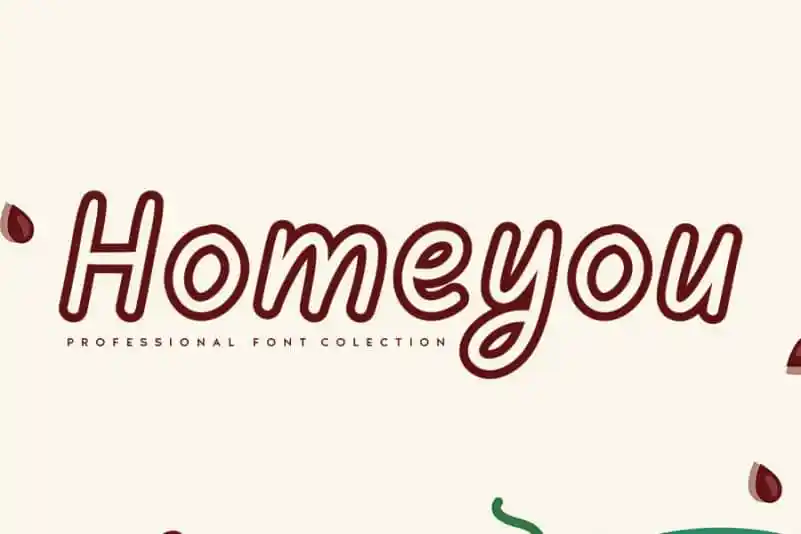
Homeyou Display Font – Fonte Grátis
Homeyou Display Font
A fonte ‘Homeyou Display Font’ é um entusiasmante acréscimo para designers que buscam uma solução elegante e única para seus projetos digitais. Com seu estilo retrô de mão escrita, Homeyou oferece o melhor dos dois mundos – a clareza moderna associada à delicadeza do traço humano. Este fonte é perfeito para quem busca criar designs originais e impressionantes. Andikastudio criou uma fonte que mantém a essência amigável da escrita sem perder o caráter moderno e sofisticado de um design digital. Homeyou Display Font é ideal tanto para gráficos digitais quanto para mídias impressas, garantindo uma harmonia perfeita entre seu uso em elementos visuais e sua consistente legibilidade, especialmente no tamanho grande necessário para designs de display. Composta por traços suaves e detalhes sutis que permitem uma escrita natural, Homeyou Display Font não apenas atende aos desejos de designers apaixonados por estilos mais humanizados em seu trabalho, mas também oferece uma maneira inteligente de expressar suas ideias de forma autêntica. Numa era digital cada vez mais avançada e tecnologicamente orientada, a Homeyou Display Font é um lembrete da importância da personalização e do toque humano que adorna até os mais modernos projetos digitais.